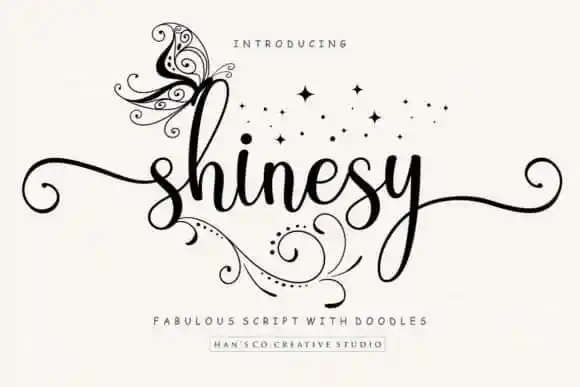
Introduzimos a nova fonte Shinesy Calligraphy, perfeita para aqueles que procuram uma pitada elegante e moderna em suas criações digitais. Esta font foi cuidadosamente criada pelo HansCo e apresentada pela 99designs. Ideal tanto para design de redes sociais como para projetos DIY com letra calligrafia, essa font transforma ideias criativas num verdadeiro trabalho de arte. Com um toque de elegância na escrita manual cuidadosamente criada, a Shinesy Calligraphy é perfeita para aqueles que buscam uma ressaltar-se de maneira chique e moderna em suas criações. Seja você designer de redes sociais ou amante do DIY, essa font irá tornar seus ideais artísticos ainda mais belos e únicos. Ainda não experimentou o poder da Shinesy Calligraphy? É hora de mergulhar nessa fonte elegante que pode transformar qualquer projeto em algo especial. Seja para uma postagem no Instagram ou um DIY, essa font traz a magia da escrita manual com estilo moderno e sofisticado. Não perca mais tempo – seu próximo design pode ser uma verdadeira obra de arte!